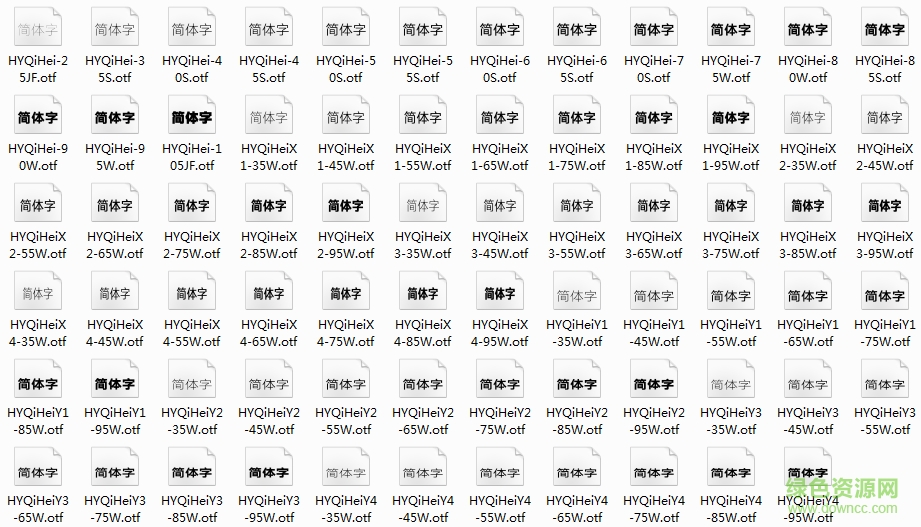
漢儀旗黑X3-55
漢儀旗黑X3-65
漢儀旗黑X3-75
漢儀旗黑X3-85
漢儀旗黑X3-95
漢儀旗黑X4-35
漢儀旗黑X4-45
漢儀旗黑X4-55
漢儀旗黑X4-65
漢儀旗黑X4-75
漢儀旗黑X4-85
漢儀旗黑Y1-35
漢儀旗黑Y1-45
漢儀旗黑Y1-55
漢儀旗黑Y1-65
漢儀旗黑Y1-75
漢儀旗黑Y1-85
漢儀旗黑Y1-95
漢儀旗黑Y2-35
漢儀旗黑Y2-45
漢儀旗黑Y2-55
漢儀旗黑Y2-65
漢儀旗黑Y2-75
漢儀旗黑Y2-85
漢儀旗黑Y2-95
漢儀旗黑Y3-35
漢儀旗黑Y3-45
漢儀旗黑Y3-55
漢儀旗黑Y3-65
漢儀旗黑Y3-75
漢儀旗黑Y3-85
漢儀旗黑Y3-95
漢儀旗黑Y4-35
漢儀旗黑Y4-45
漢儀旗黑Y4-55
漢儀旗黑Y4-65
漢儀旗黑Y4-75
漢儀旗黑Y4-85
漢儀旗黑Y4-95
漢儀旗黑是由三個(gè)系列字體(長(zhǎng)、方、扁)組成的一個(gè)龐大而完整的家族字體,從最細(xì)的25到最粗的105,共計(jì)15個(gè)字重,是迄今為止國(guó)內(nèi)最大、最豐富的字重的家族字體,可以滿(mǎn)足企業(yè)多渠道,全方位的內(nèi)容設(shè)計(jì)以及定制化需求,實(shí)現(xiàn)企業(yè)品牌形象在各渠道的統(tǒng)一呈現(xiàn)。
筆畫(huà)設(shè)計(jì)
設(shè)計(jì)簡(jiǎn)約、爽朗富有時(shí)代氣息固然重要,但我們?cè)谠O(shè)計(jì)時(shí)不能忘卻字的民族性和傳統(tǒng)文化,筆劃必須要有內(nèi)涵。
筆畫(huà)設(shè)計(jì)中融入了書(shū)寫(xiě)的韻味,采用“陰陽(yáng)線(xiàn)”的處理方法,講究線(xiàn)條之美,使筆劃挺拔有力,剛?cè)嵯酀?jì)。
通過(guò)筆畫(huà)的粗細(xì)變化,賦予字體不同的性格與表現(xiàn)力,但“骨子里”卻是“一家人”,線(xiàn)條勁道,緊致。
結(jié)構(gòu)設(shè)計(jì)
UD設(shè)計(jì)盡可能減少多余的修飾元素,將除字形識(shí)別以外的信息量將至最低,盡可能避免過(guò)大的弧度為閱讀所帶來(lái)的不穩(wěn)定感,更方便視覺(jué)障礙者的閱讀。
西文設(shè)計(jì)
漢儀旗黑的西文設(shè)計(jì)沿用了與著名字體helvetica和Univers相同的Neo-grotesque字形風(fēng)格。Neo-grotesque類(lèi)字形簡(jiǎn)潔勻質(zhì)硬朗,可以與旗黑的中文部分達(dá)成非常良好的配合。
命名方式
漢儀旗黑作為一款家族字,創(chuàng)新性地運(yùn)用了西方字體系統(tǒng)化字庫(kù)的使用和命名方式,使設(shè)計(jì)師字體選擇的過(guò)程更輕松便捷